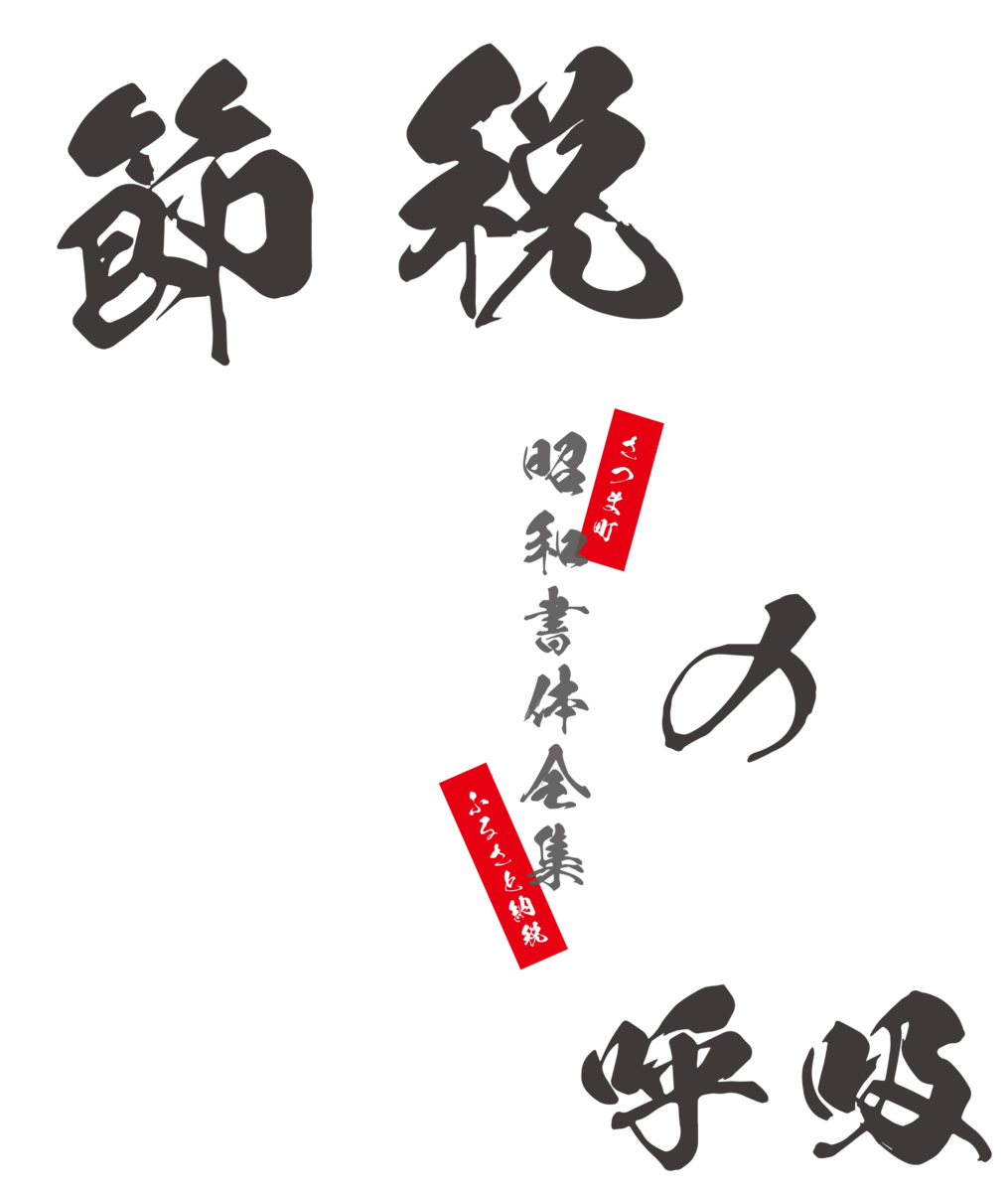
昭和書体全集がをさつま町のふるさと納税返礼品としてリリース
鹿児島県さつま町は、ふるさと納税返礼品に地元出身の書家であり、地元から全国に向け毛筆フォントを発信してきた、昭和書体の専属書家であった「綱紀栄泉」氏の死去に際し、遺言となった「私の文字を一人でも多くの人に使って頂きたい」との思いを受け制作された、最高傑作集「昭和書体全集210書体収録DVD」を、これまでの「昭和書体全書体セット」と入れ替えることを発表した。
「昭和書体全集210書体収録DVD」は、同社専属書家であった「綱紀栄泉」の死去に際し、栄泉の遺した「全国の人たちに一人でも多く使って頂きたい、そのためにもっと安く」ということを遺言と捉え、昭和書体の全ての毛筆フォントをまとめて、高ボリュームのDVD2枚組にして、尚且つこれまでに無い低価格を実現して発売を開始。
さつま町は、当町のPRにもなり、地域の発展に繋がるとして当該商品を返礼品に加えたことを発表。
▼さつま町ふるさと納税担当者からの一言
昭和書体様のご協力により、全国で始めてふるさと納税にフォントを出品することができました。
以前の全書体セットからフォント数を増やし、このセットだけでさまざまな場面の文字を彩ることができるさつま町自慢の逸品となっております!